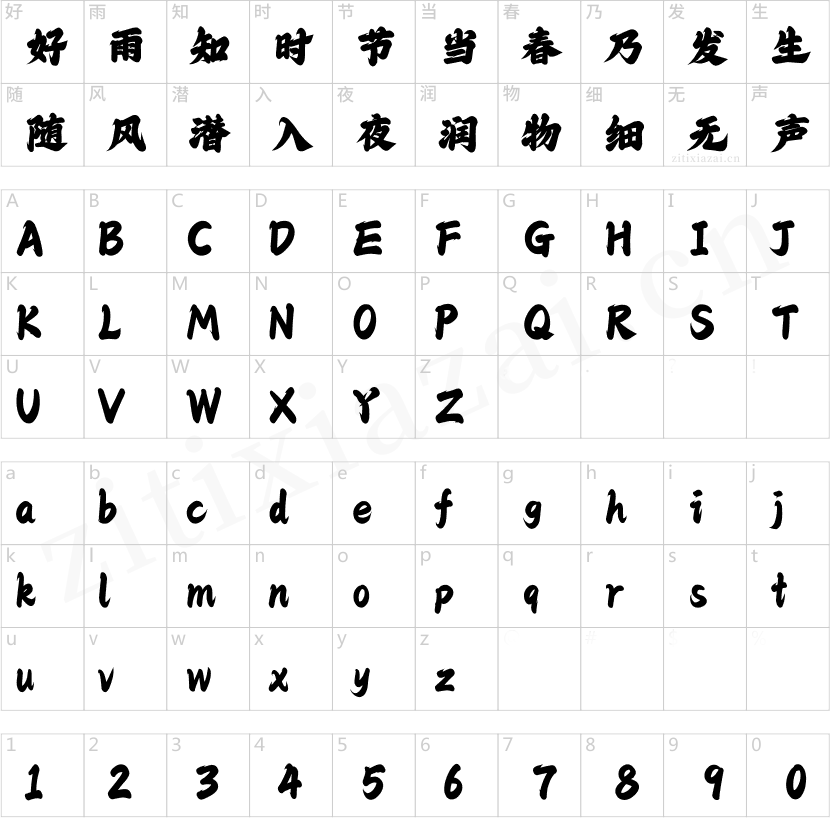
Aa龙砚体
Aa龙砚体字体
Aa龙砚体是一款非常具有艺术性的字体,它的设计灵感来源于对古典艺术的研究,同时又融入了现代字体设计的元素。字形优美,笔画粗细变化自然,给人以大气、典雅的感觉。Aa龙砚体是一款既传统又现代的字体,它的设计充满艺术感,美观大方,实用性也非常强。无论是对于设计师还是对于普通读者来说,都是一种非常不错的字体选择。Aa龙砚体适合用于具有艺术感的场合,比如海报、宣传单张、书籍封面等。由于其字形流畅且具有动态感,也适合用于大量的文本排版,如报纸、杂志等。